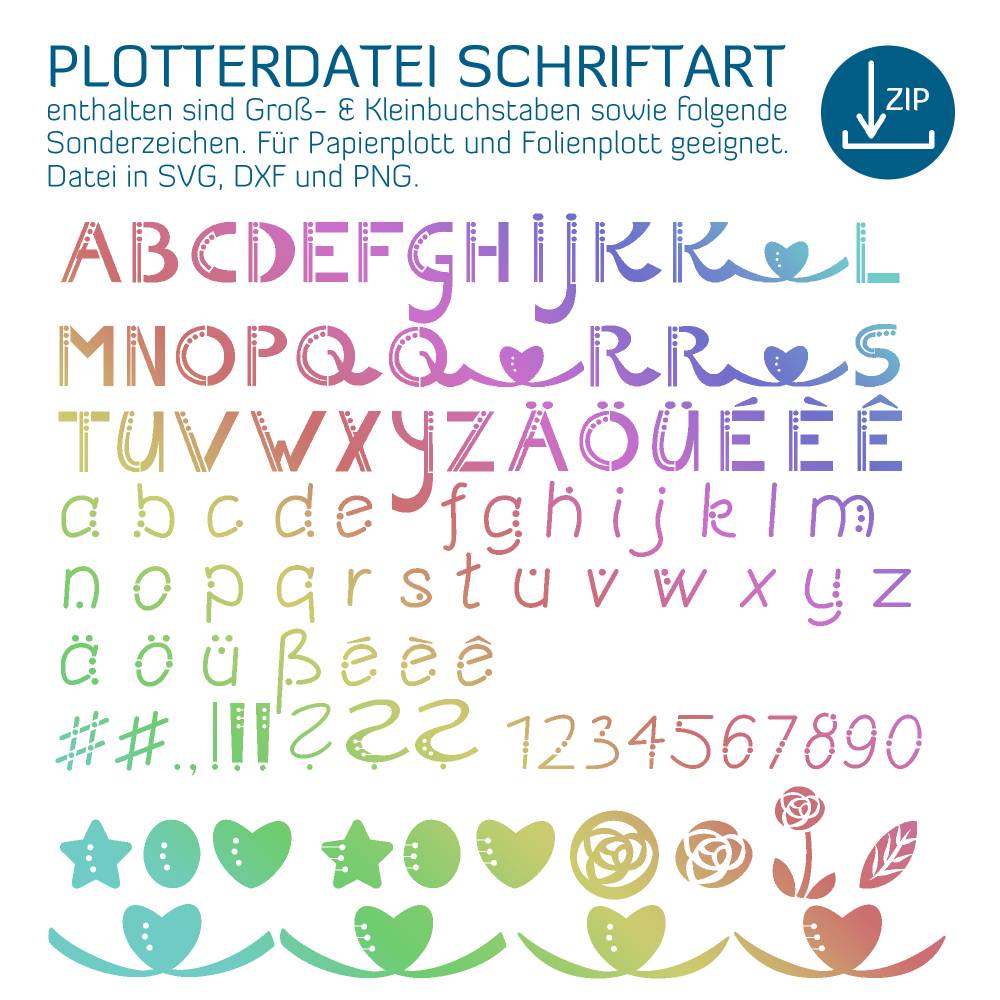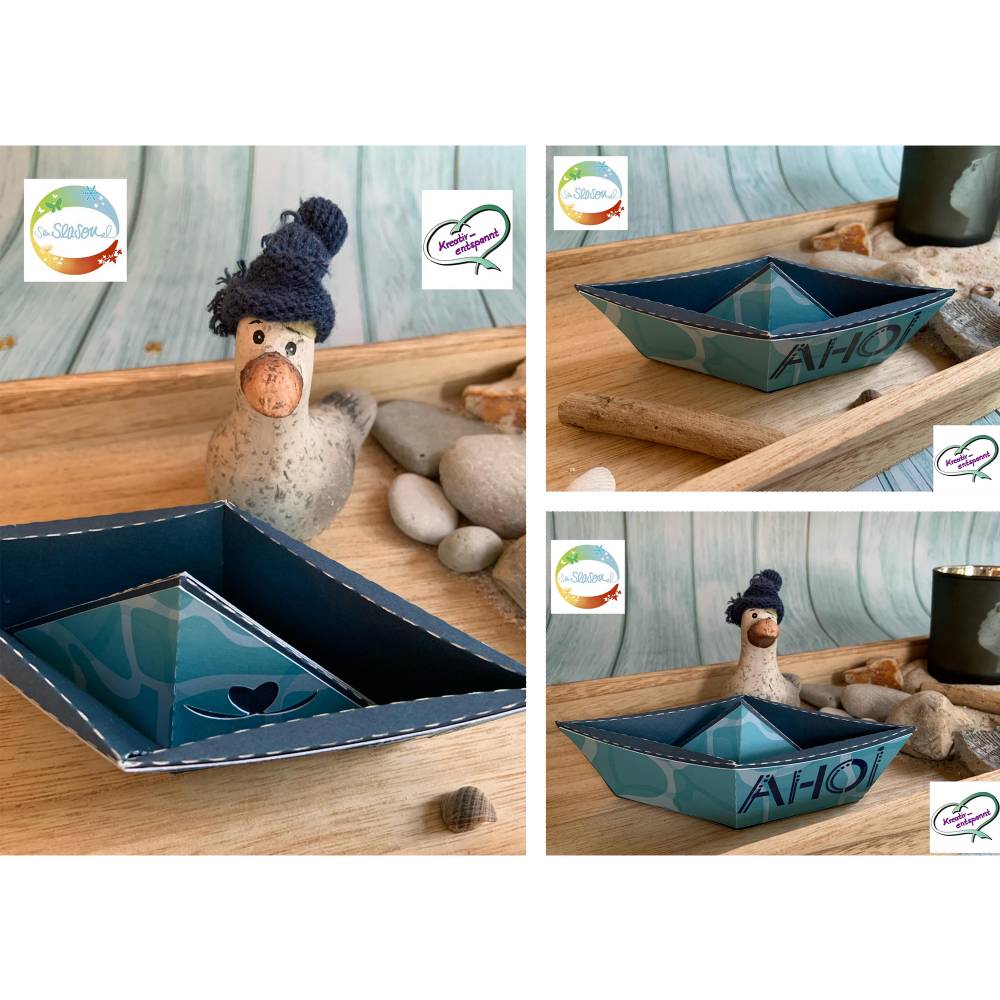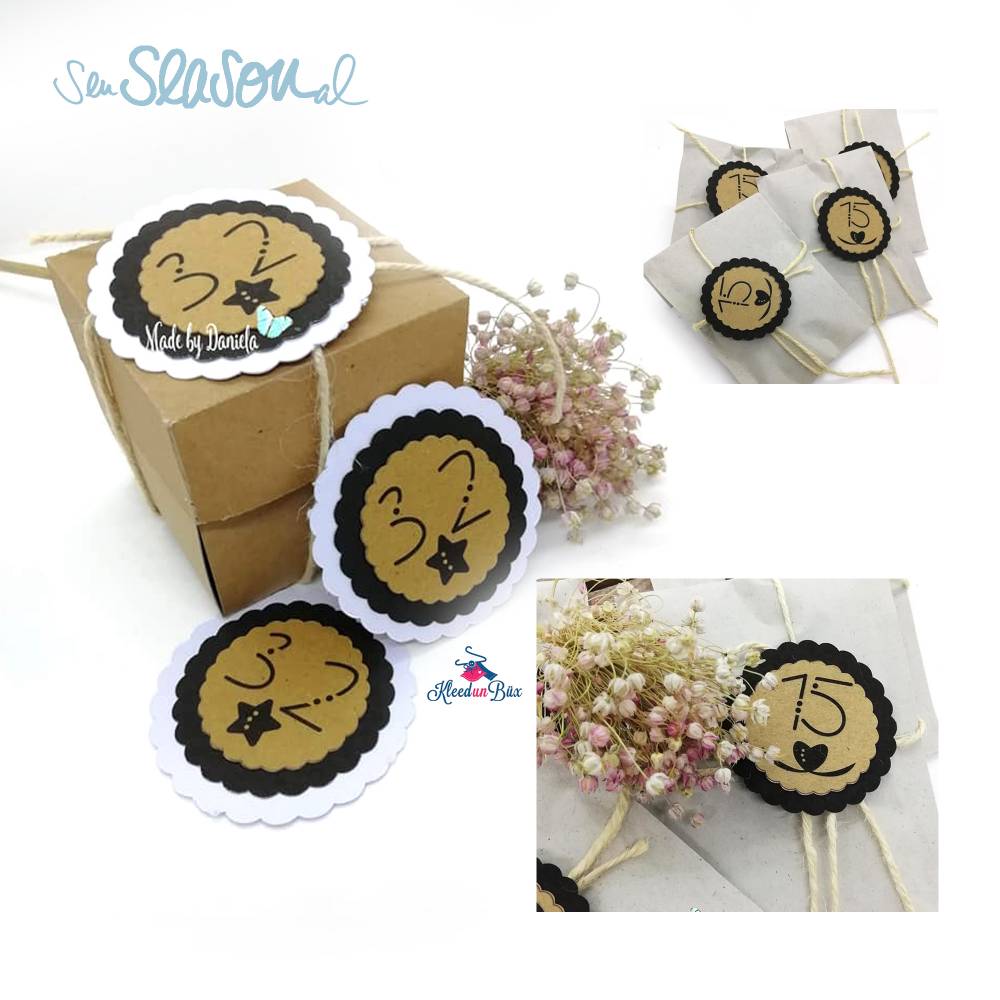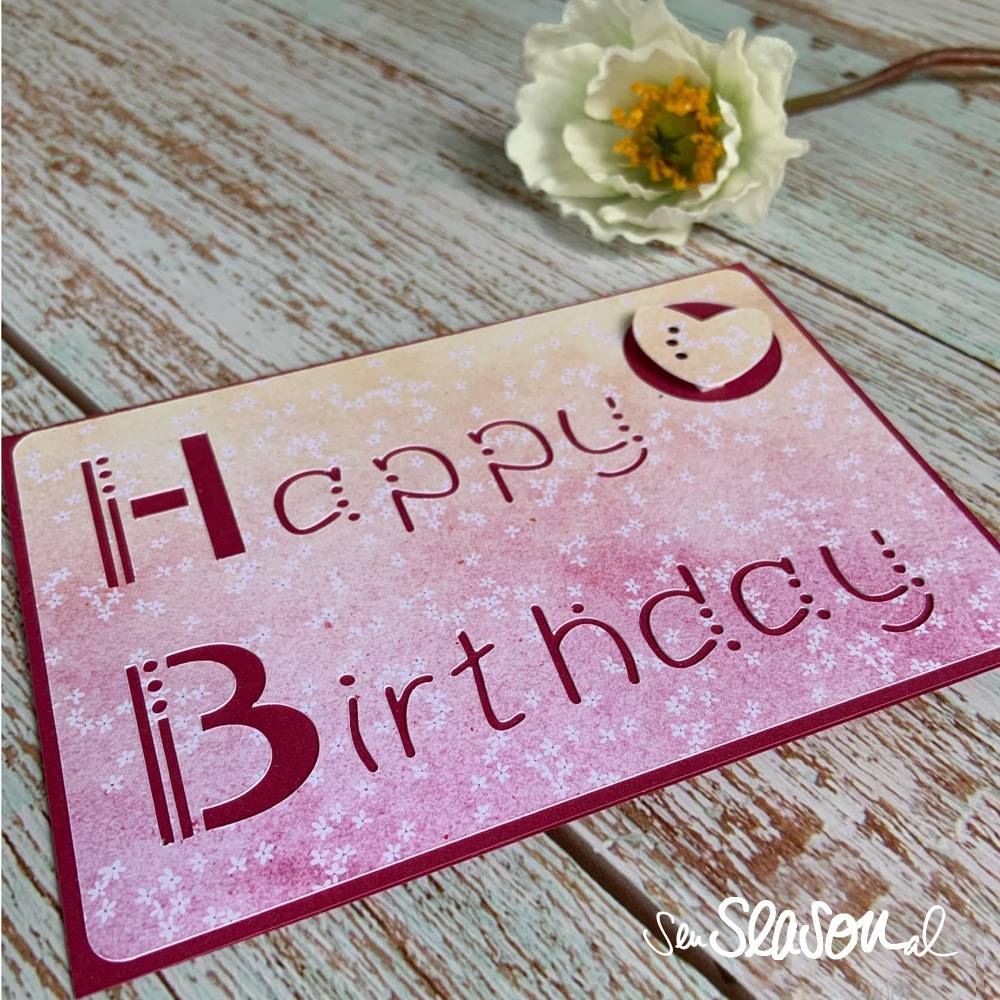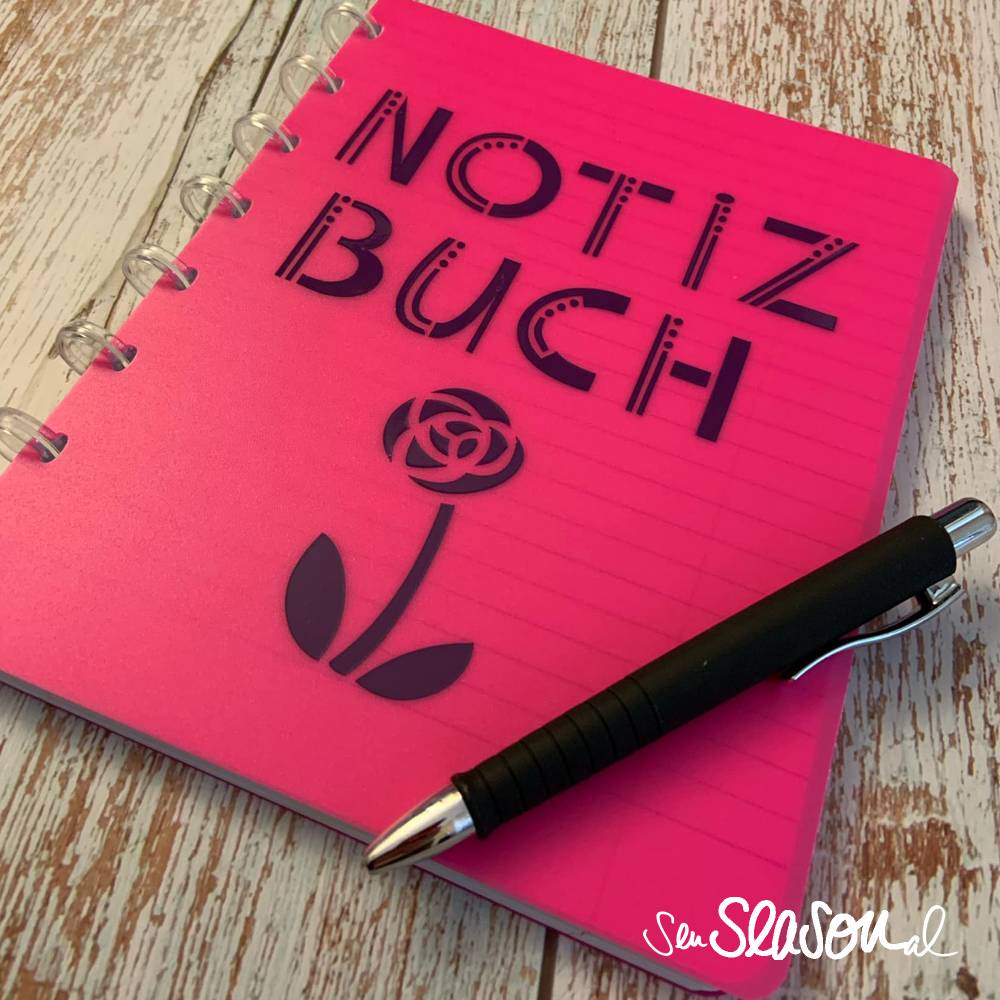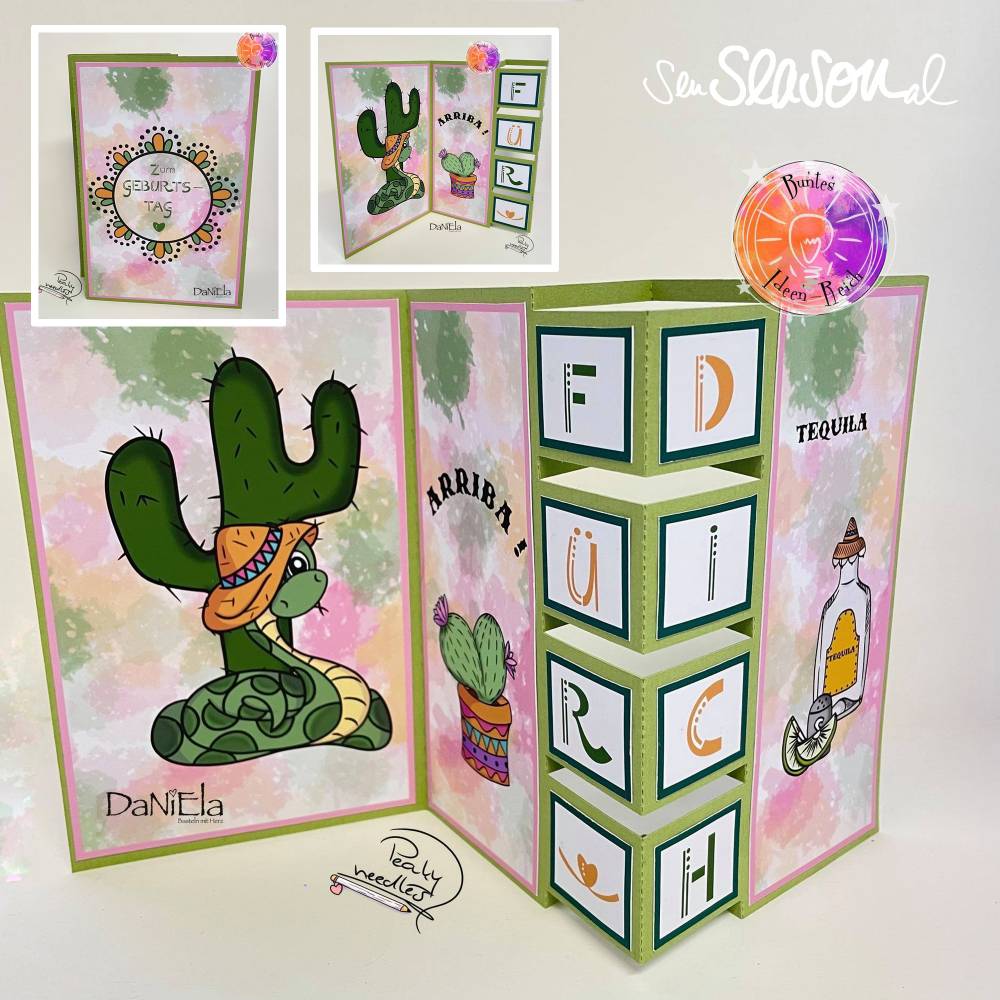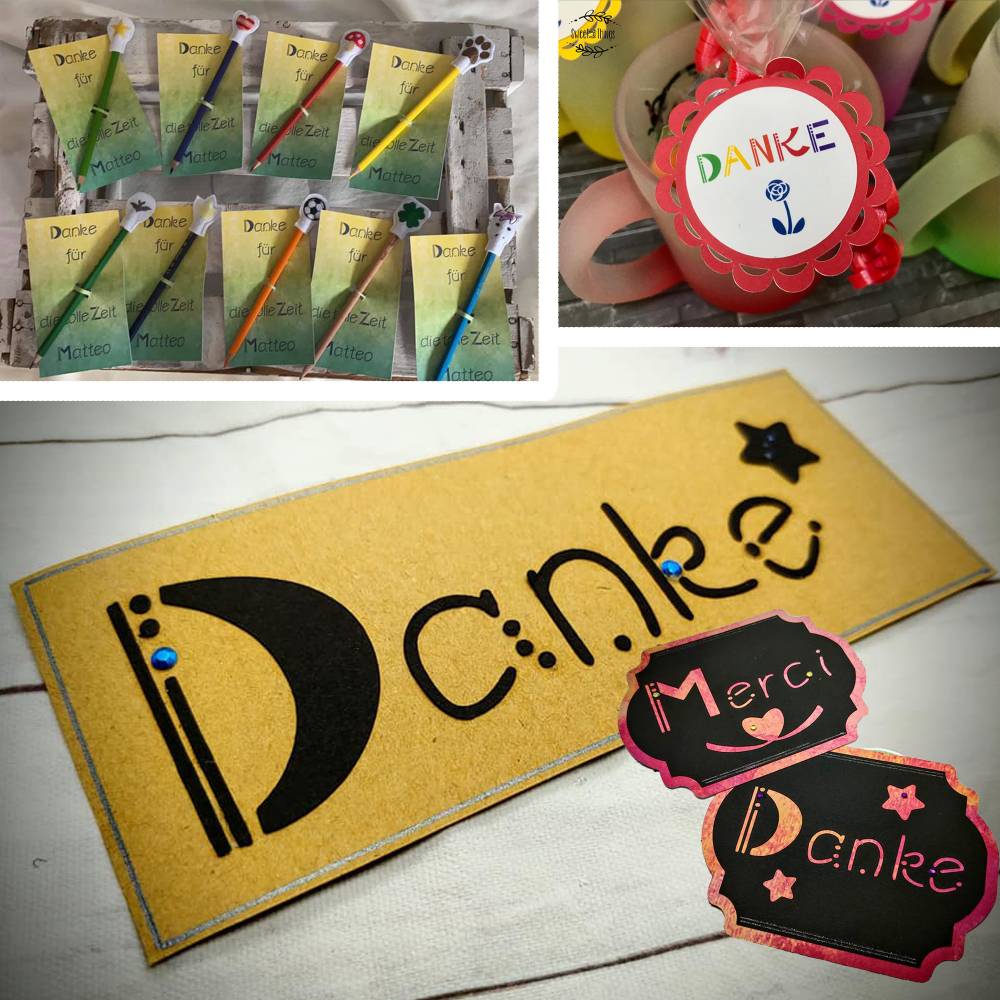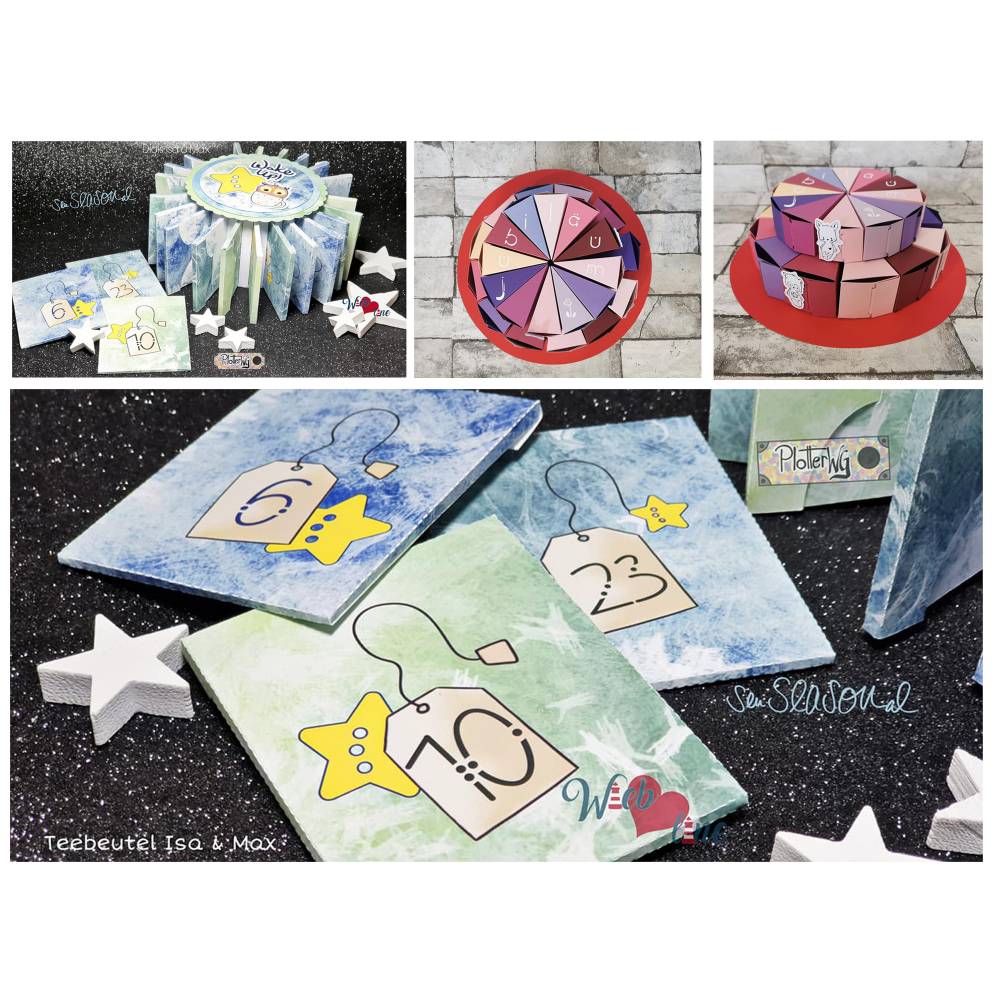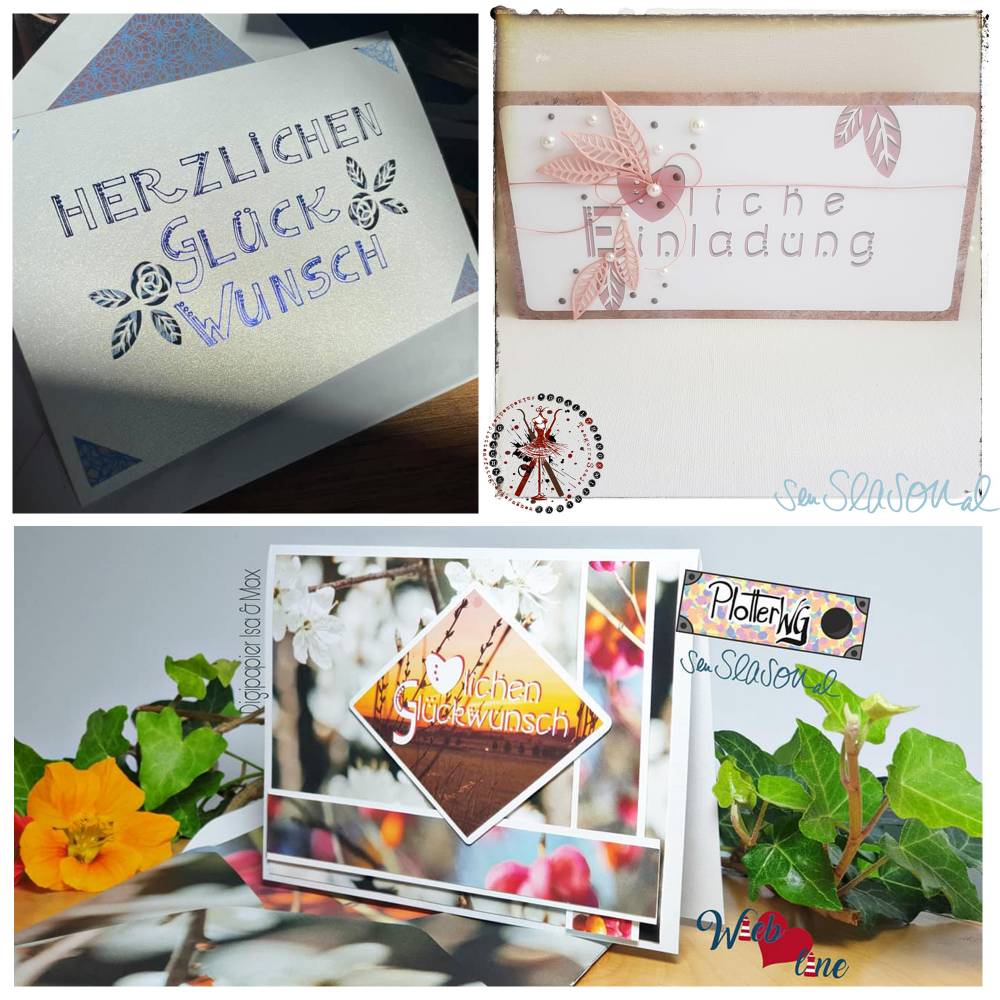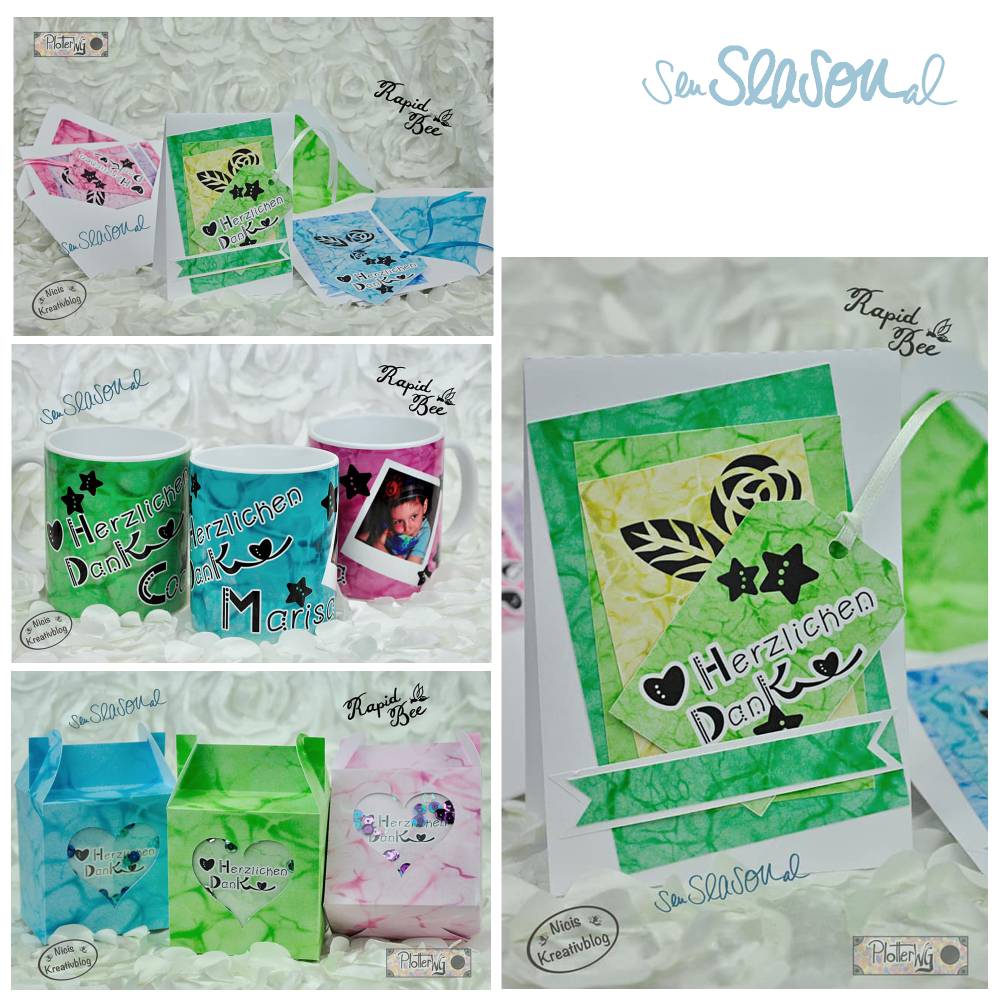
Plotterdatei Schriftart optimiert für den Papierplott, auch für Folienplott, Plott-Datei als svg, dxf von senSEASONal
Die Plotterdatei Schriftart ist perfekt für das Plotten mit Papier. Dabei ist sie außergewöhnlich, schlicht und trotzdem elegant. Das Besondere: Es fallen beim Papier plotten keine Einzelteile mehr heraus, alle Buchstaben sowie die Sonderzeichen sind für den Papierplott optimiert.
Selbstverständlich ist diese außergewöhnliche Schriftart auch für den Folienplott geeignet. In der Bildergalerie siehst du einige Beispiele - sowohl mit Papier, als auch mit Folie oder als Digistamp genutzt. Im Lookbook, das den Dateien beiliegt, findest du nochmal alle Ideen gebündelt als Anregungen zum Nachmachen.
Enthalten sind alle großen und kleinen Buchstaben, sowie einige Sonderzeichen. In der Bildergalerie findest du eine Übersicht über die beinhalteten Elemente. Die Schriftart liegt in SVG und DXF vor. Du setzt die Wörter aus einzelnen Buchstaben in deiner Wunschgröße zusammen und kannst sie danach für deine geplotteten Karten oder andere Plott-Projekte als besonderen Hingucker einsetzen.